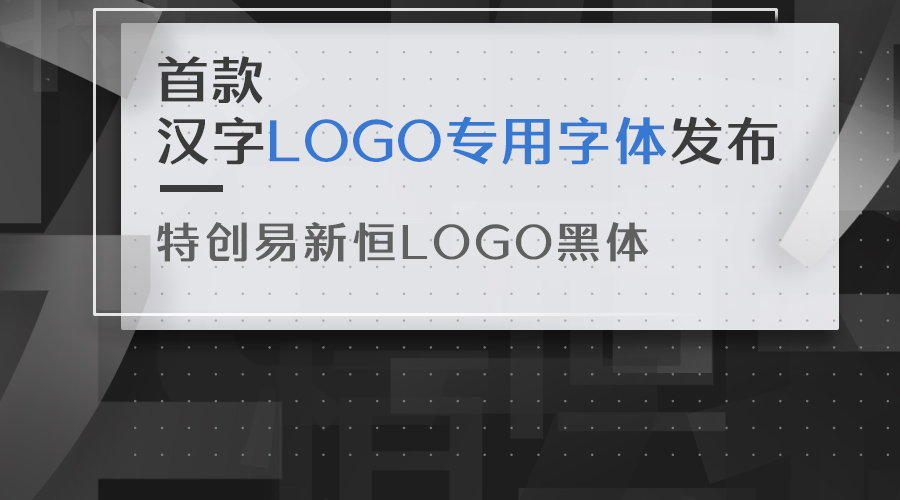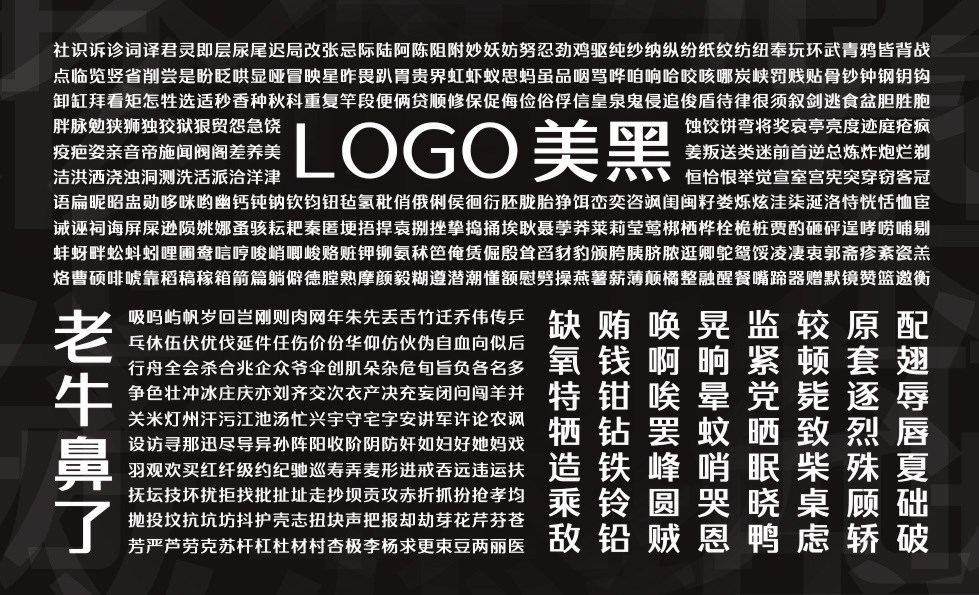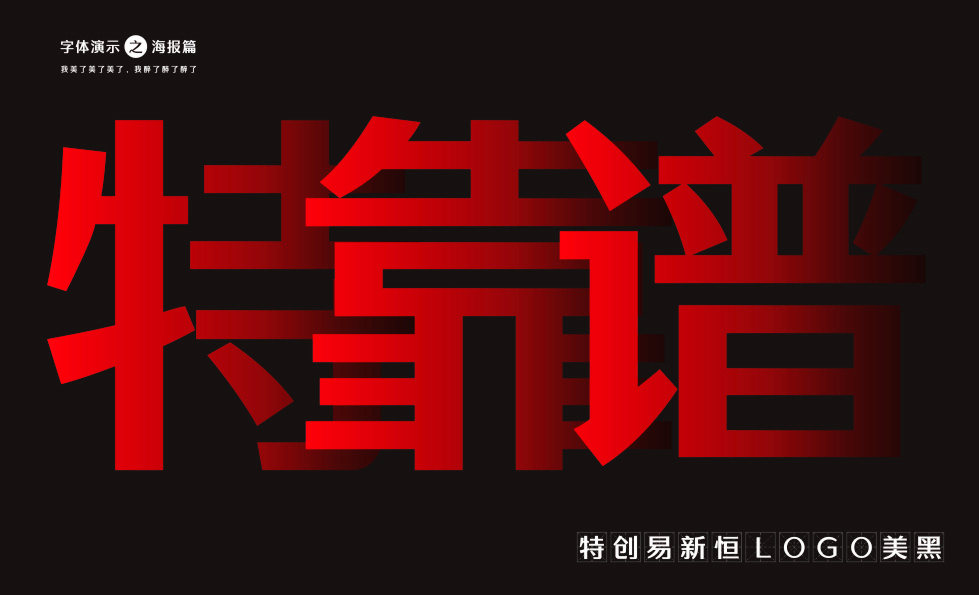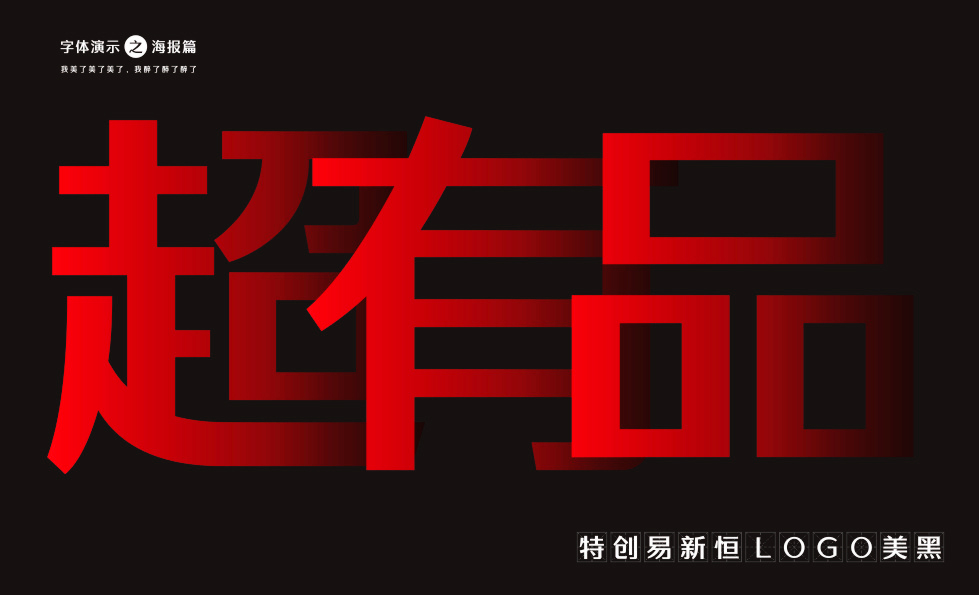
特创易委托而定制设计的一款LOGO专用字体
本款字体是受特创易委托而定制设计的一款LOGO专用字体,该字体前期定制了3千多个常用汉字,大小写英文以及常用符号;后续可能会增补二级常用字。本字体完全结合中文LOGO应用场景,融纳了黑体等线稳定的骨架与宋体粗细有秩的笔势,字形上保留了黑体的庄重,又结合了宋体的骏朗。在撇、捺、弯、勾等诸多细节上摒弃了大多数汉字正文字体的繁复,取而代之的是极简会意的笔画处理,从而获得现代LOGO汉字所需的简洁与永恒性。